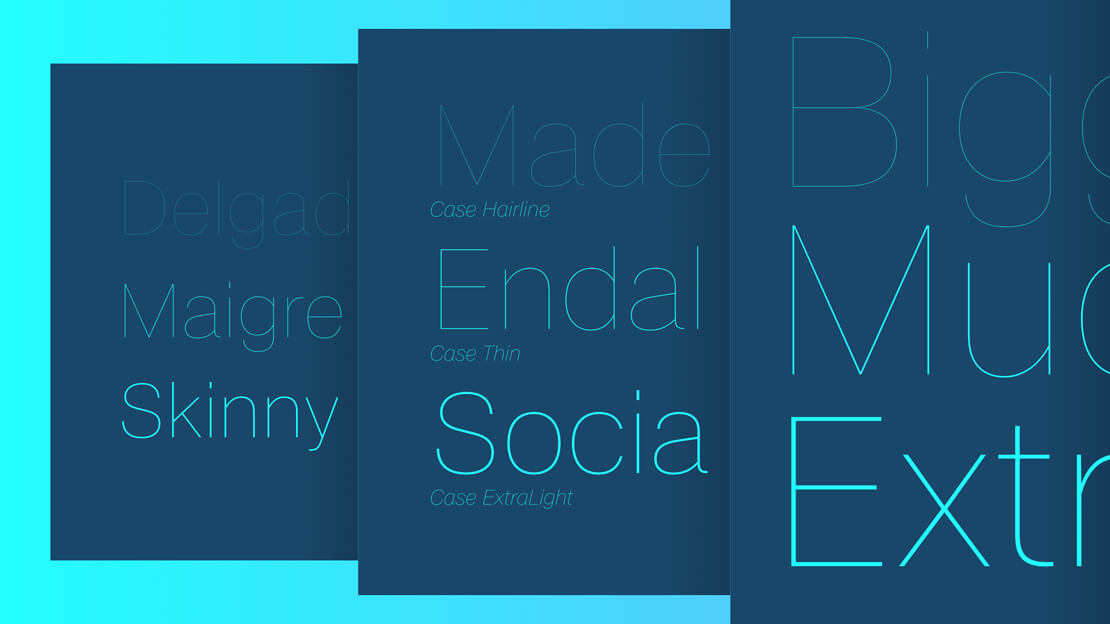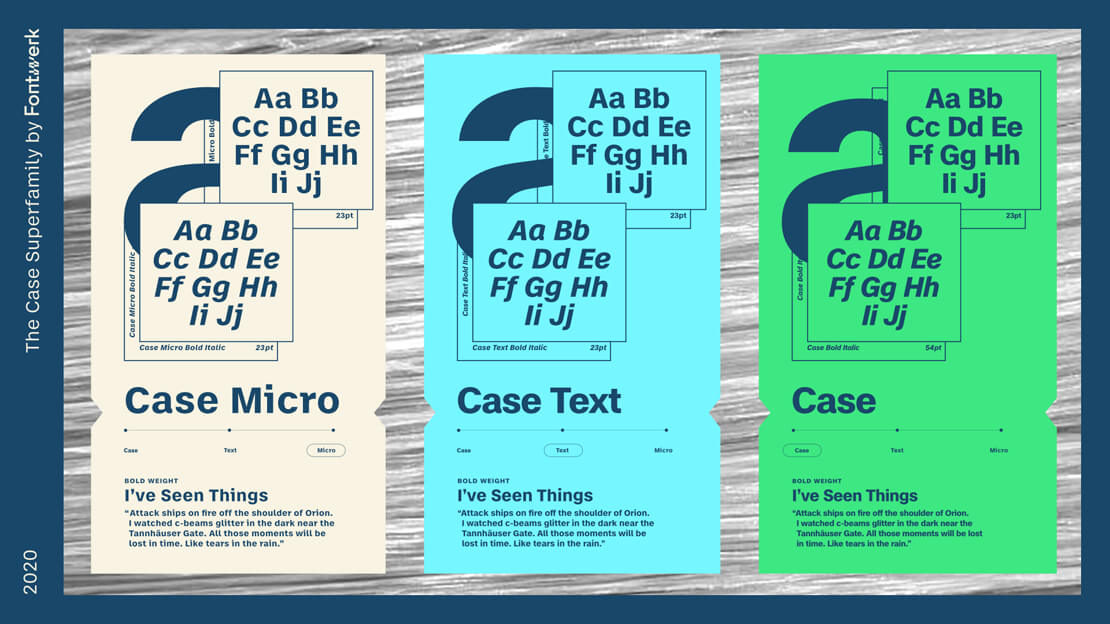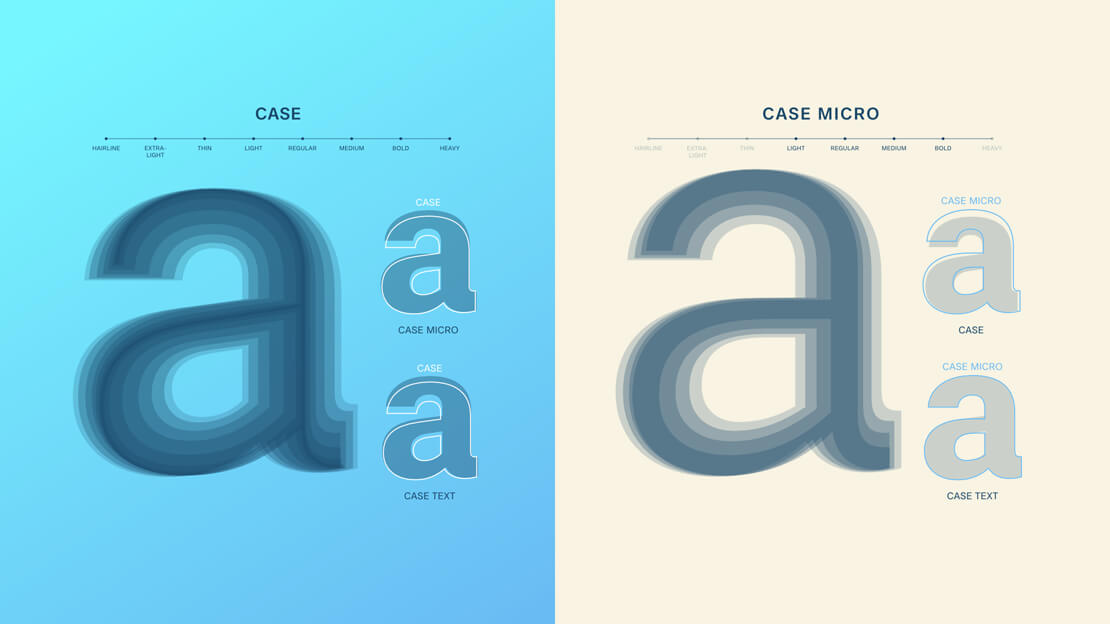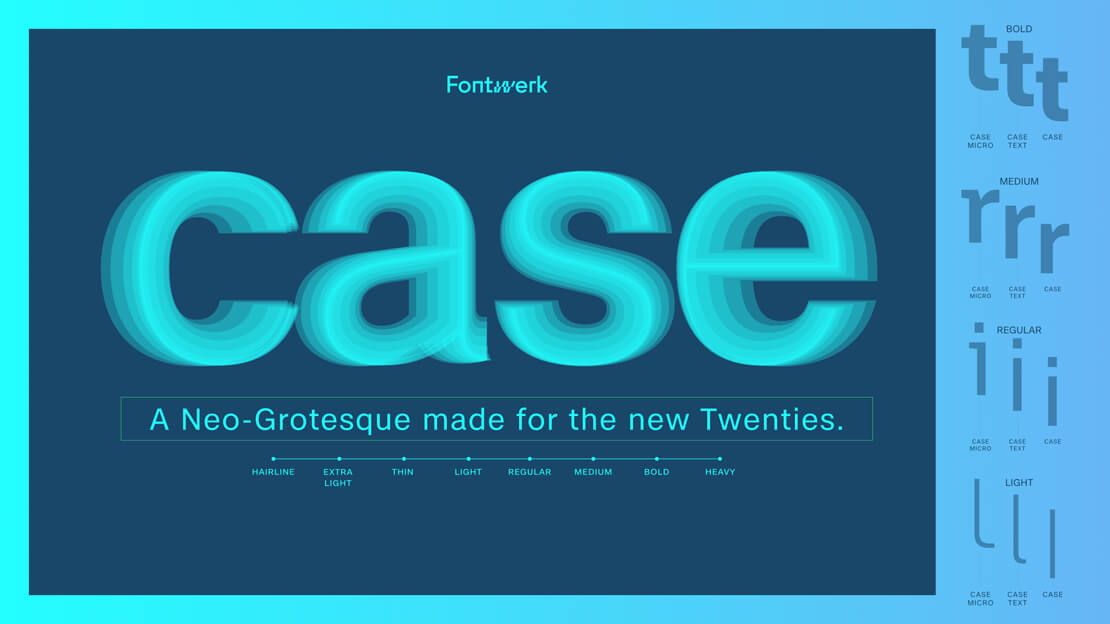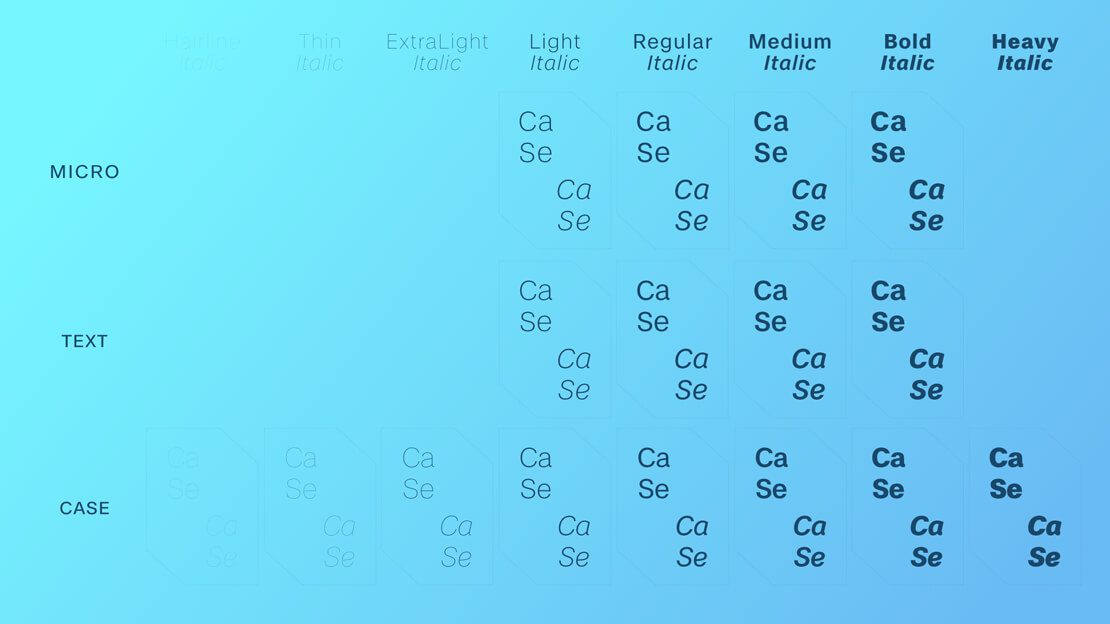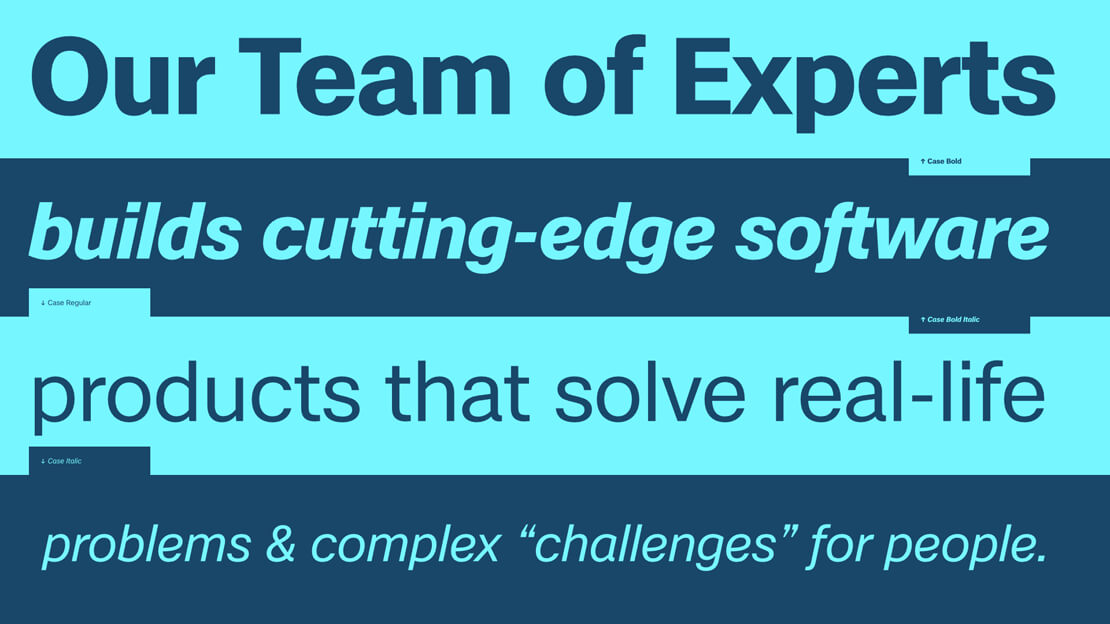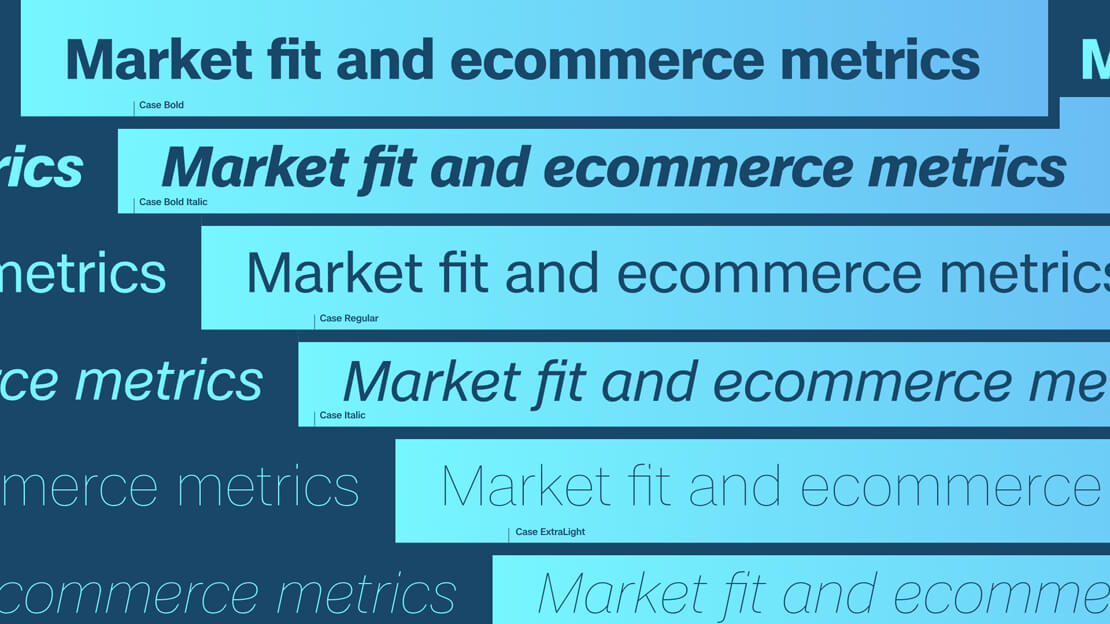
Case: Moderne Neo-Grotesk für die neuen Zwanziger
Erik Spiekermann hat sich gemeinsam mit Anja Meiners und Ralph du Carrois dem Genre der Neo-Grotesk-Schriftarten gewidmet und eine moderne Variante gestaltet. Das Ergebnis dieser vier Jahre währenden Zusammenarbeit ist die »Case«.
Die drei Typedesigner haben den Grundcharakter der Schriftfamilie bewusst so gestaltet, dass er vertraut wirkt und zudem auch Vertrauen schaffen soll. »Alles, was sie am Genre der populärsten Schriftart der Welt für verzichtbar halten, ließen sie weg. Alles, was sie an ihr lieben, ist drin«, so der Schriftenanbieter Fontwerk, der »Case« frisch aufgenommen hat.
Die neue Neo-Grotesk soll sich somit für eine starke Markenbildung eignen. Eine Schrift, die aus der Praxis komplexer Branding-Projekte für die Praxis solcher Branding-Projekte entstand. Ihre 32 Einzelschnitte sowie die enthaltenen Variable Fonts sorgen für entsprechende Flexibilität.
Vorerst gibt es die »Case« in drei optischen Größen. Die Kernfamilie wurde für häufige Anwendungsfälle wie beispielsweise Logos, Wortmarken und Headlines konzipiert, die »Text« eignet sich für umfangreicheren Content und die »Micro« für klein gesetzte Textbereiche. Je nach Einsatzgebiet soll mit ihr noch eine Leserlichkeit bei 5pt Schriftgröße möglich sein. In manchen Fällen kann die »Micro« auch noch unterhalb von diesem Wert funktionieren.
Ein wichtiges unterscheidendes Kriterium der Familienmitglieder ist ihre jeweilige Laufweite. Im Vergleich ist die Zurichtung der normalen Case eng, die der »Text« hingegen weiter und der »Micro« am weitesten. Weitere Unterschiede zugunsten der besseren Lesbarkeit von »Case Text« und »Case Micro« sind eine höhere x-Höhe, ein »l mit Schniepel« (offizielle Spiekermann-Terminologie) und offenere Formen als bei ihrer großen Schwester. Die Micro besitzt zusätzliche unterscheidbarere Zeichenformen (r, i, j) bzw. breitere Glyphen (f, t), sowie deutliche Kontraste in den Zusammenflüssen von Stamm und Bogen.
Der Name der Schrift leitet sich übrigens aus einer besonderen Eigenschaft aller Case-Stile ab: die Abschlüsse von Zeichen wie c, a, s, e und ihrer Artverwandten befinden sich auf gleicher Höhe. Dies dient der Optimierung für die Gestaltung von Logos und Wortmarken.